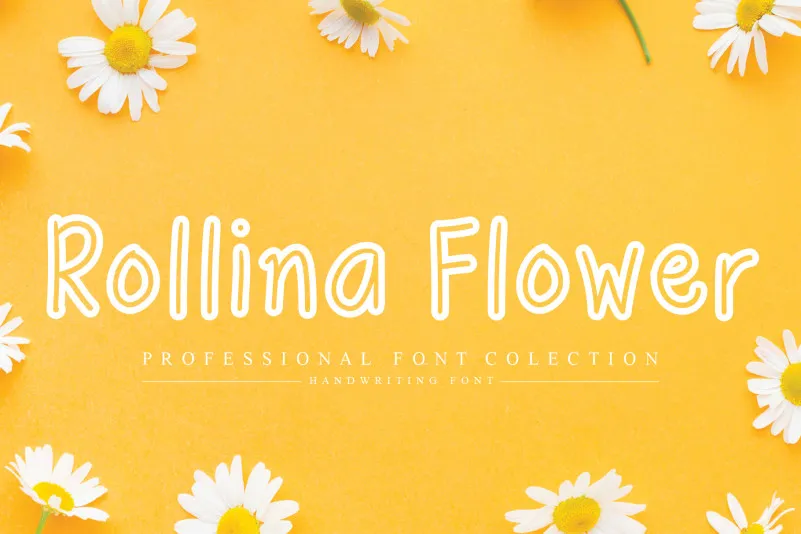
Rollina Flower Display Font – Download Grátis
A fonte Rollina Flower Display é uma elegante e simples fonte escrita a mão que encanta os amantes da criação artística. Esta fonte única se destaca por sua versatilidade impressionante, permitindo-a ser usada de maneiras inovadoras para criar designs excepcionais. Perfeito para quem busca um toque delicado e único em suas produções gráficas, a Rollina Flower Display é uma escolha ideal para designers que desejam agregar um toque autêntico à sua marca ou projeto visual. Seja você criando cartões de visita personalizados, design de produtos ou qualquer outro trabalho gráfico, esta fonte oferece flexibilidade e originalidade, tornando-a perfeita para quem valoriza a personalização em seus materiais.